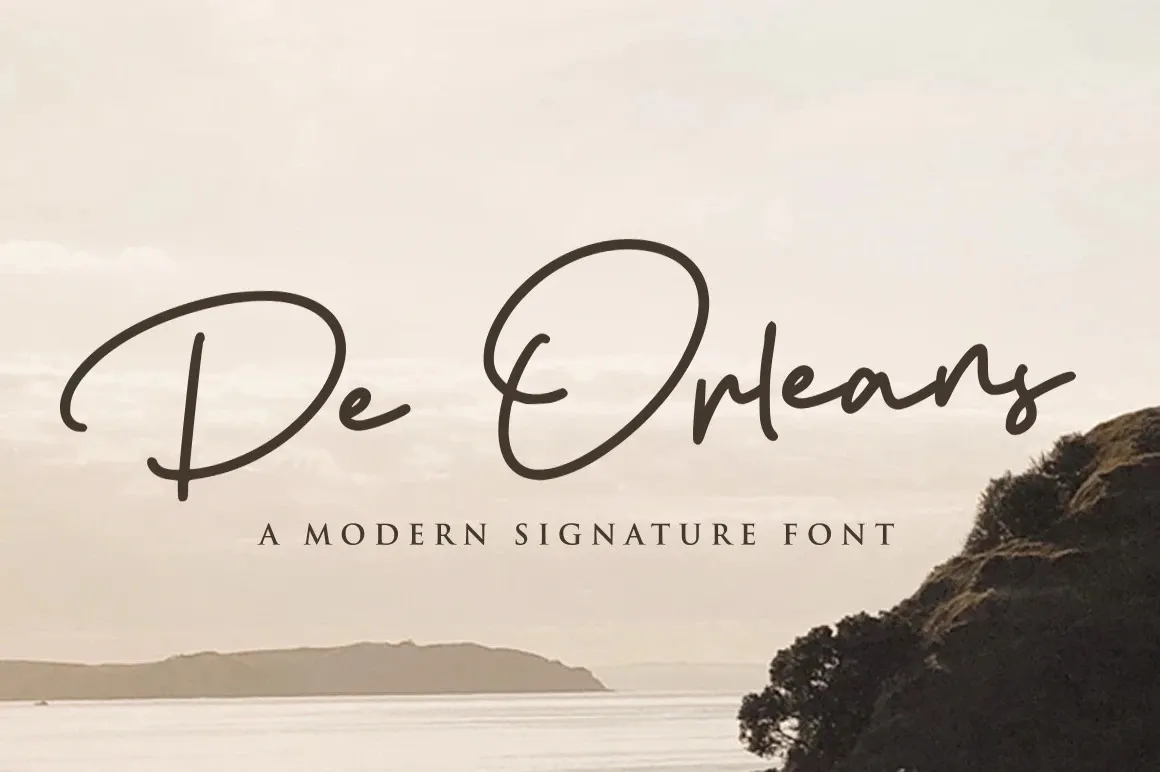
De Orleans Handwritten Font – Download Grátis
Esta é uma fonte de escrita à mão leve, projetada para dar brilho a qualquer texto que você escrever com ela. Cada letra foi cuidadosamente criada, garantindo que seu design sempre fique lindamente apresentado. Inspirada em um estilo moderno e suave de escrita à mão contemporânea, esta fonte vem equipada com ligaturas e estilos alternativos, oferecendo uma aparição única e algo especial aos seus projetos. Seja para uma logo elegante ou para adicionar um toque de personalidade em seu site, essa fonte certamente faz sua marca. Através da 99designs, acesse esta fonte de escrita à mão que promete dar o máximo em suas criações visuais.